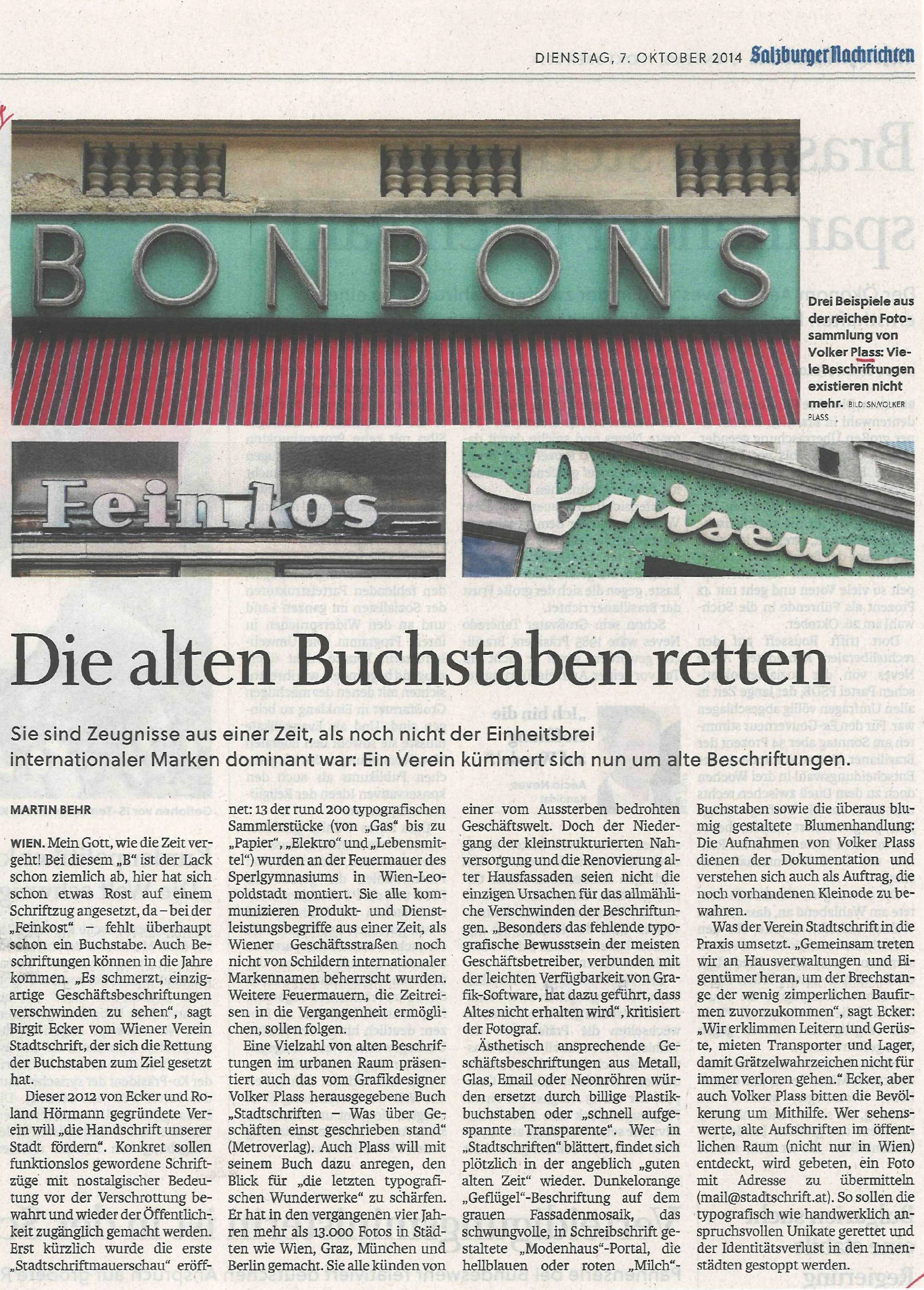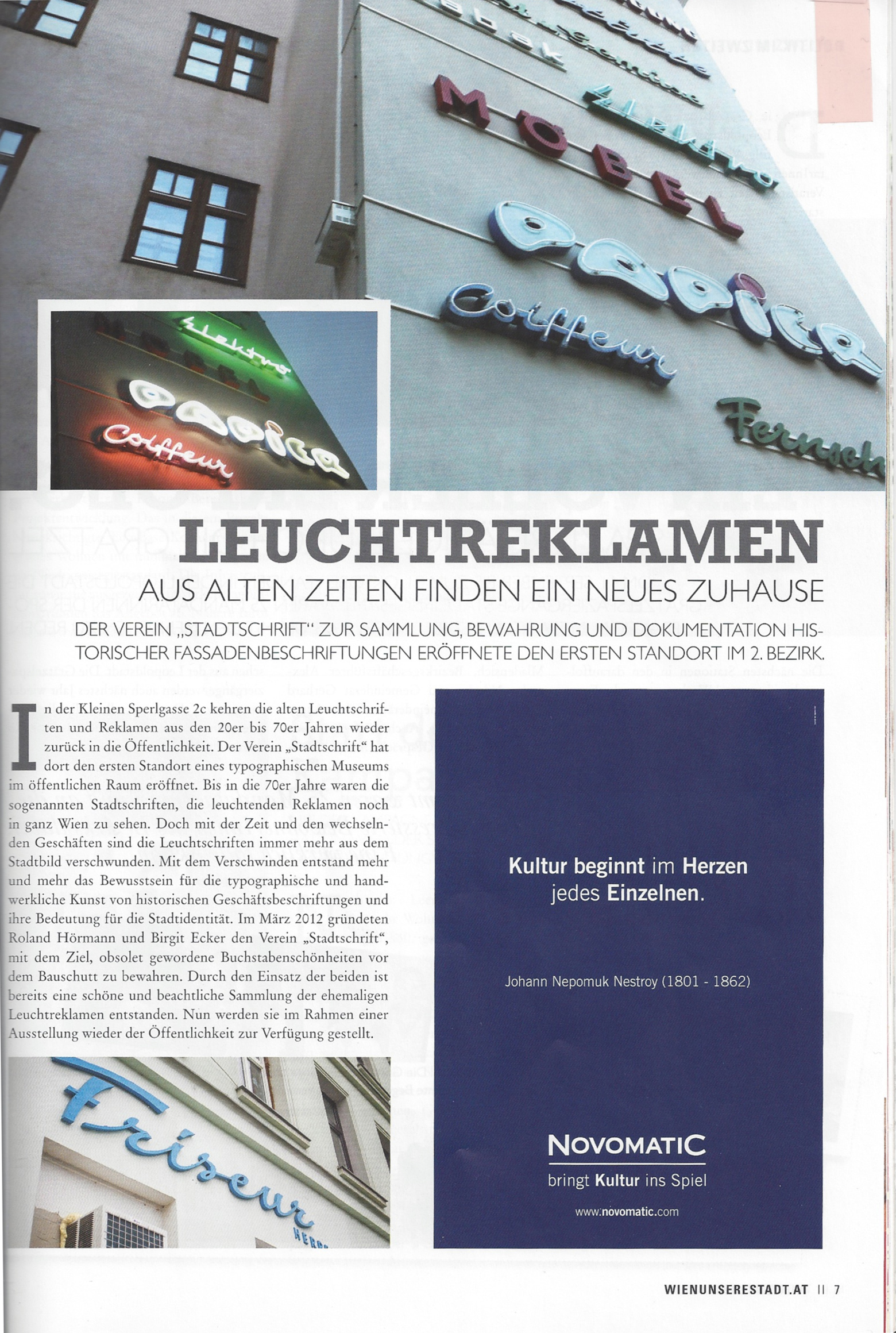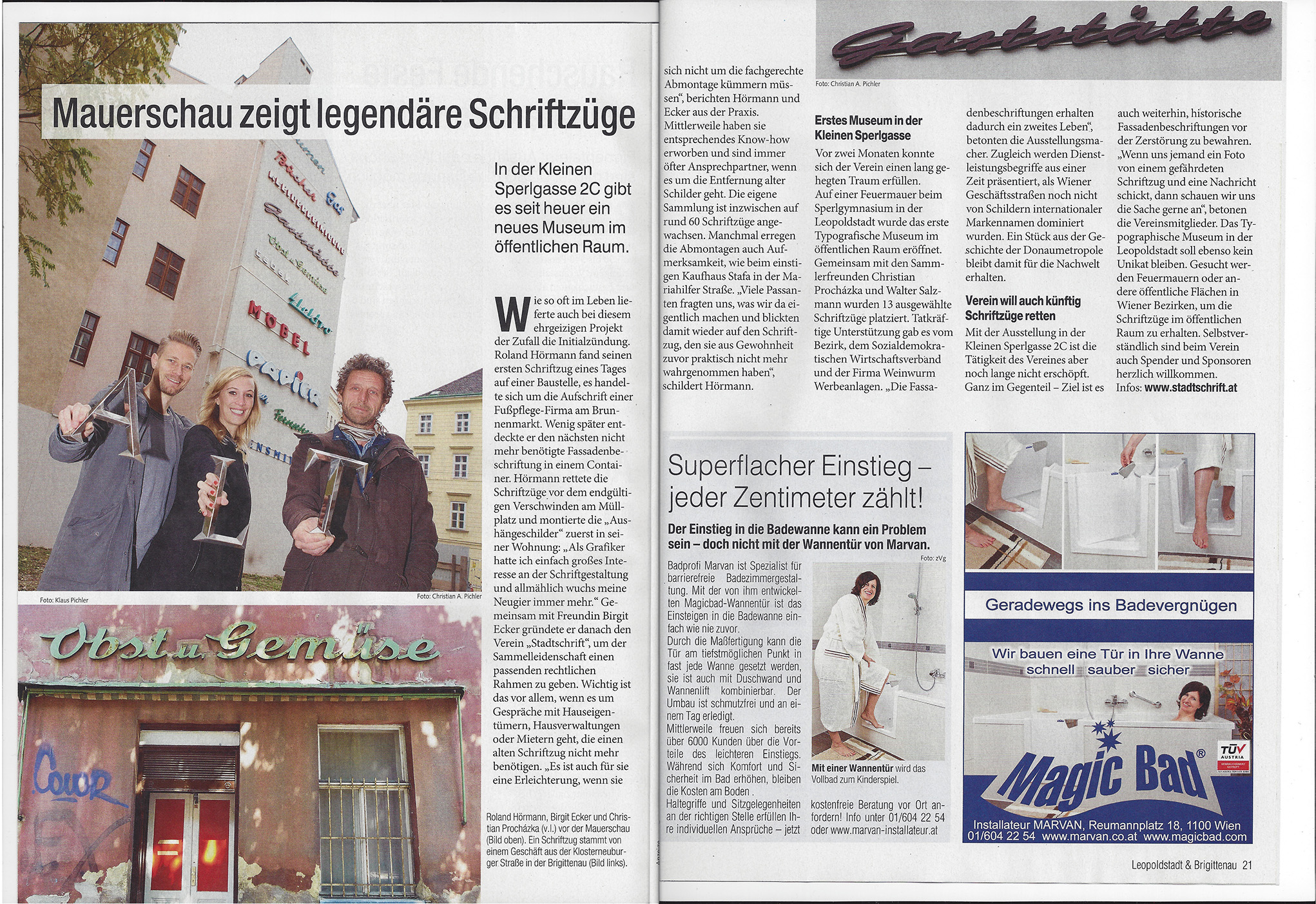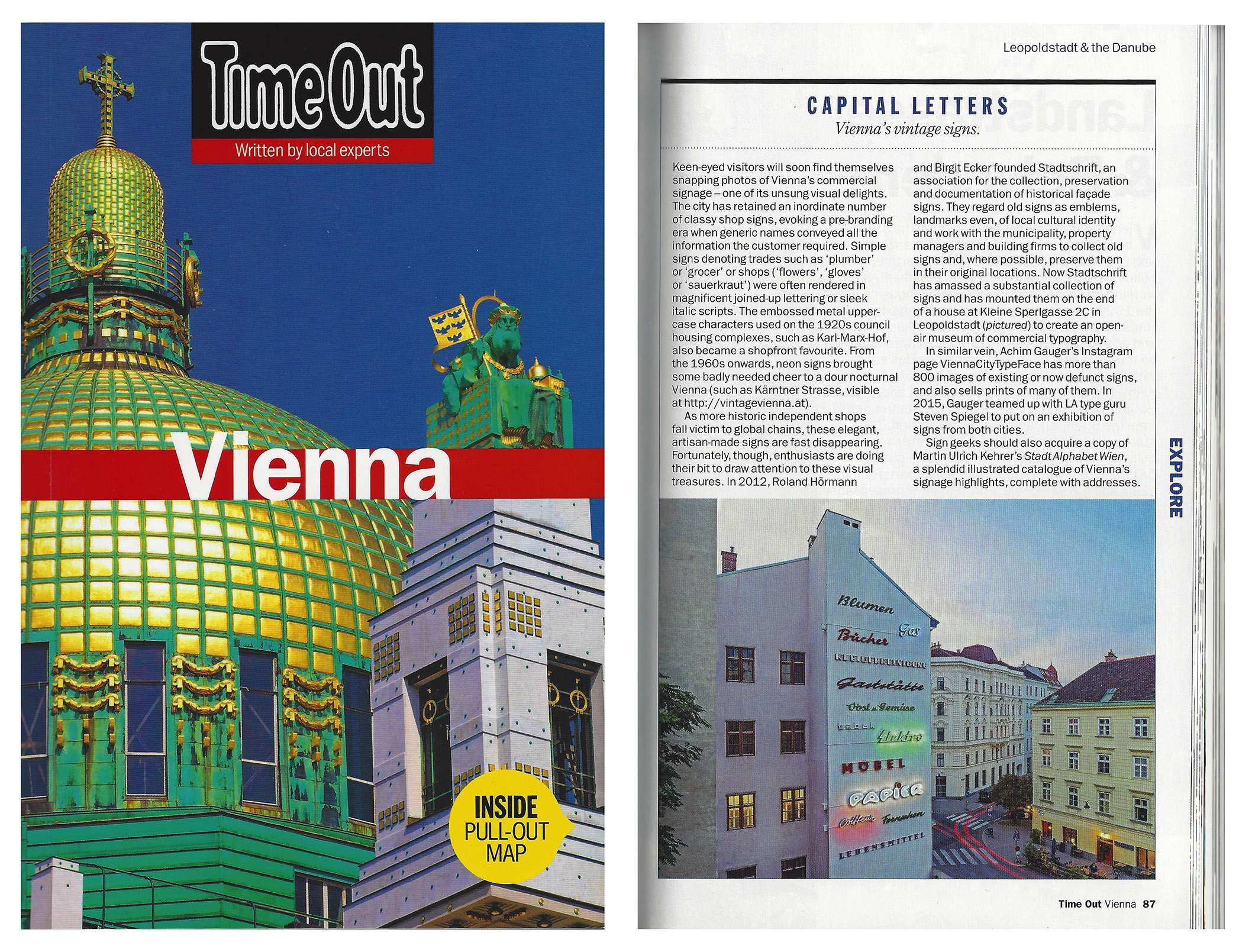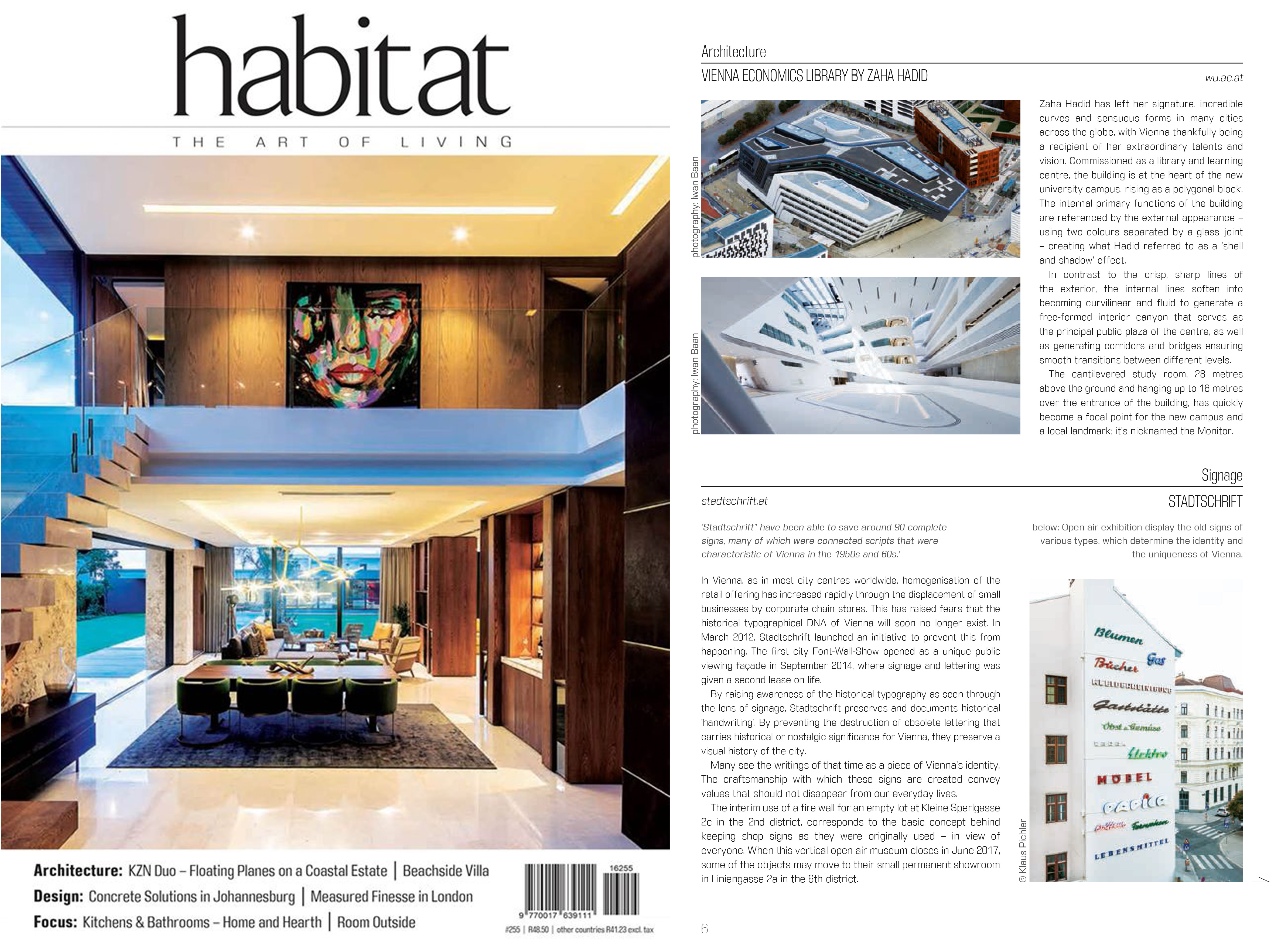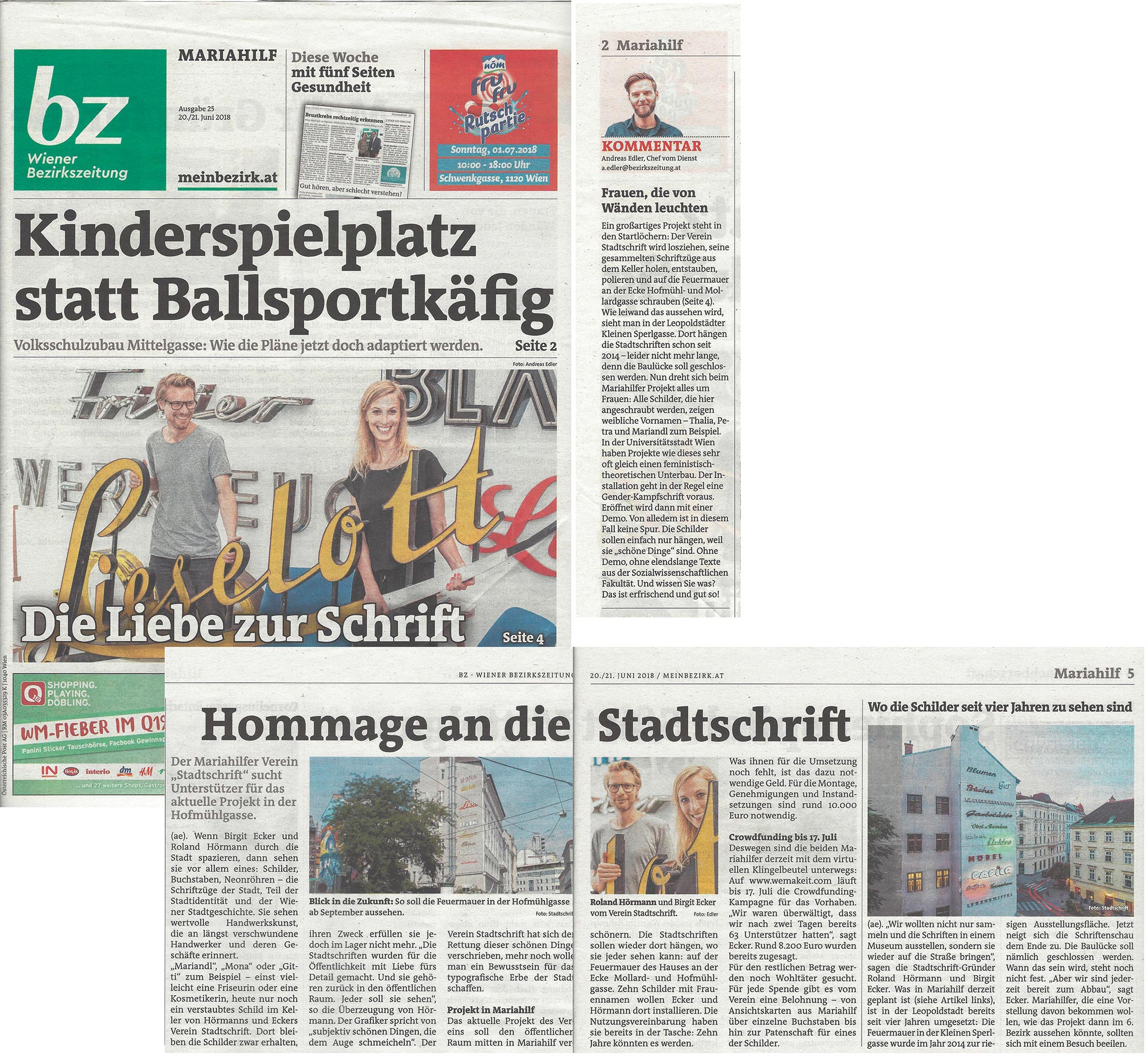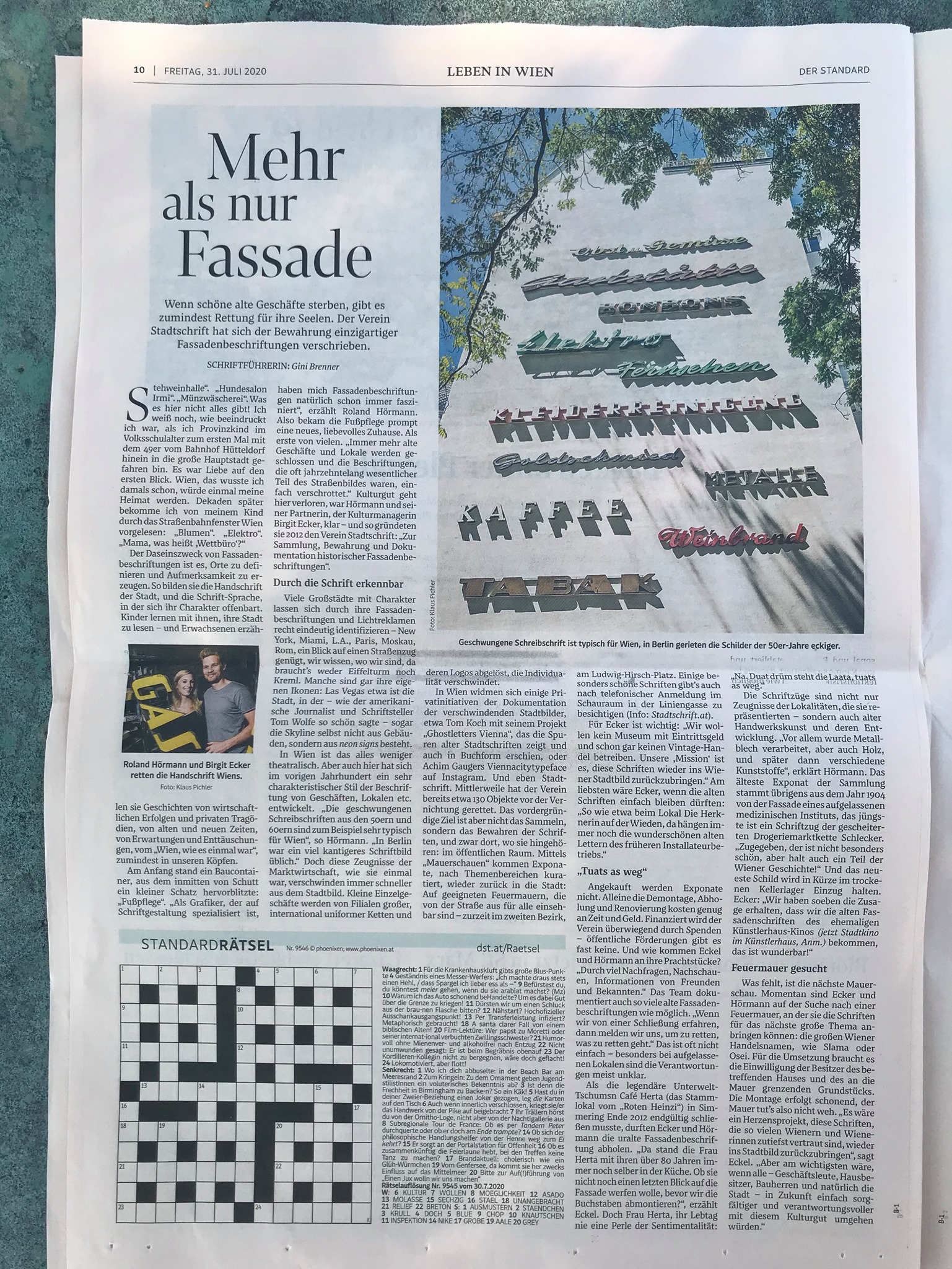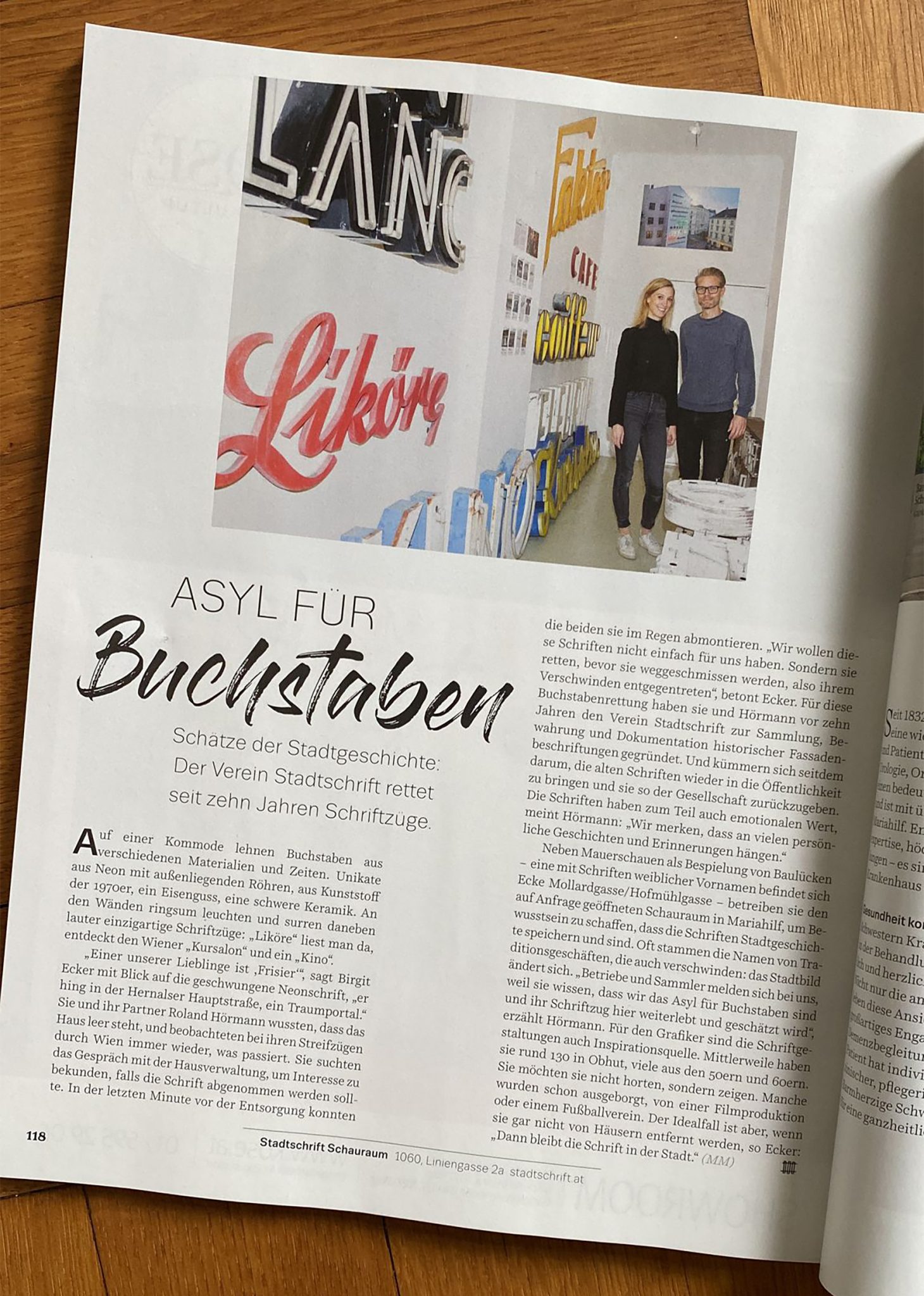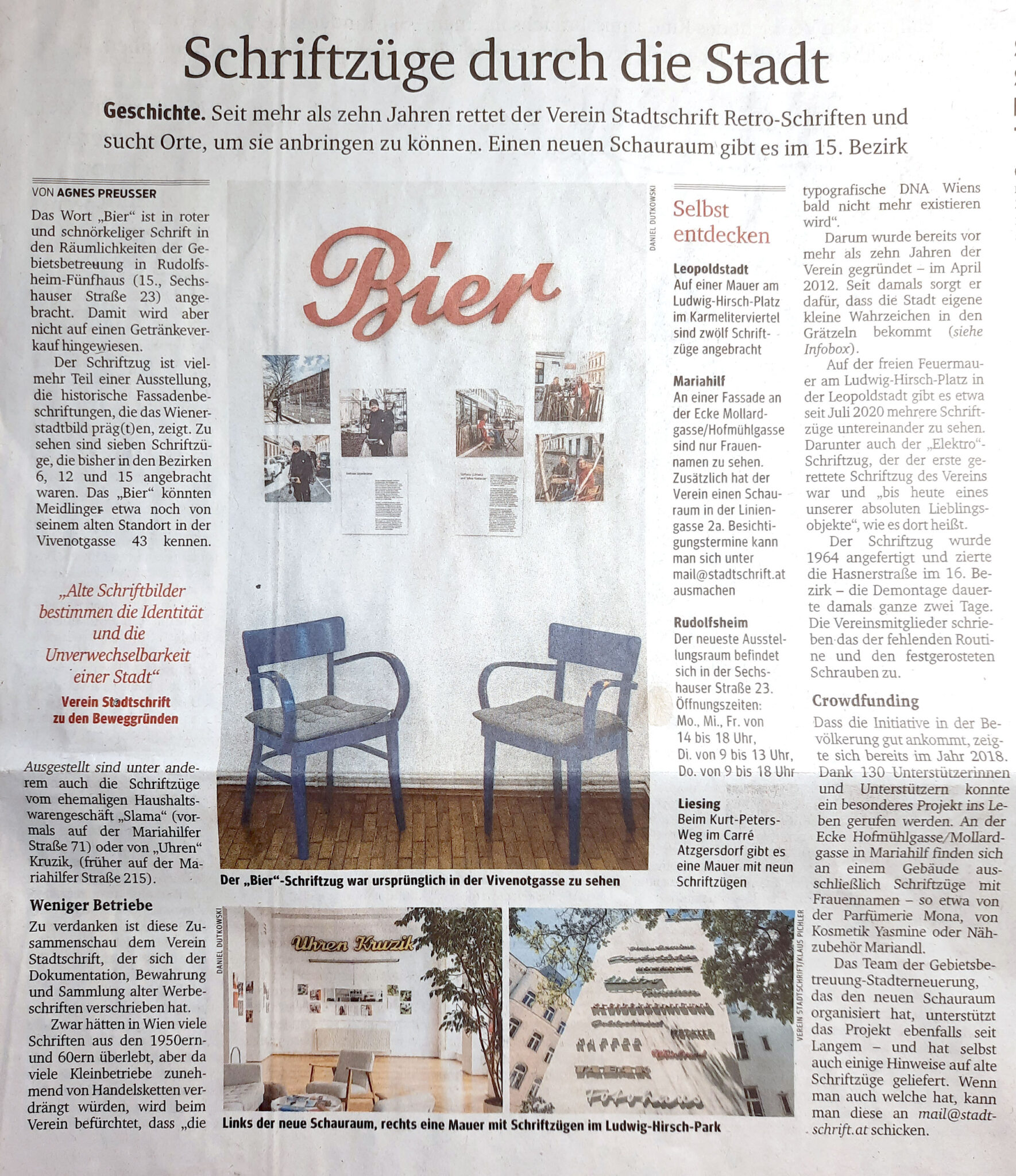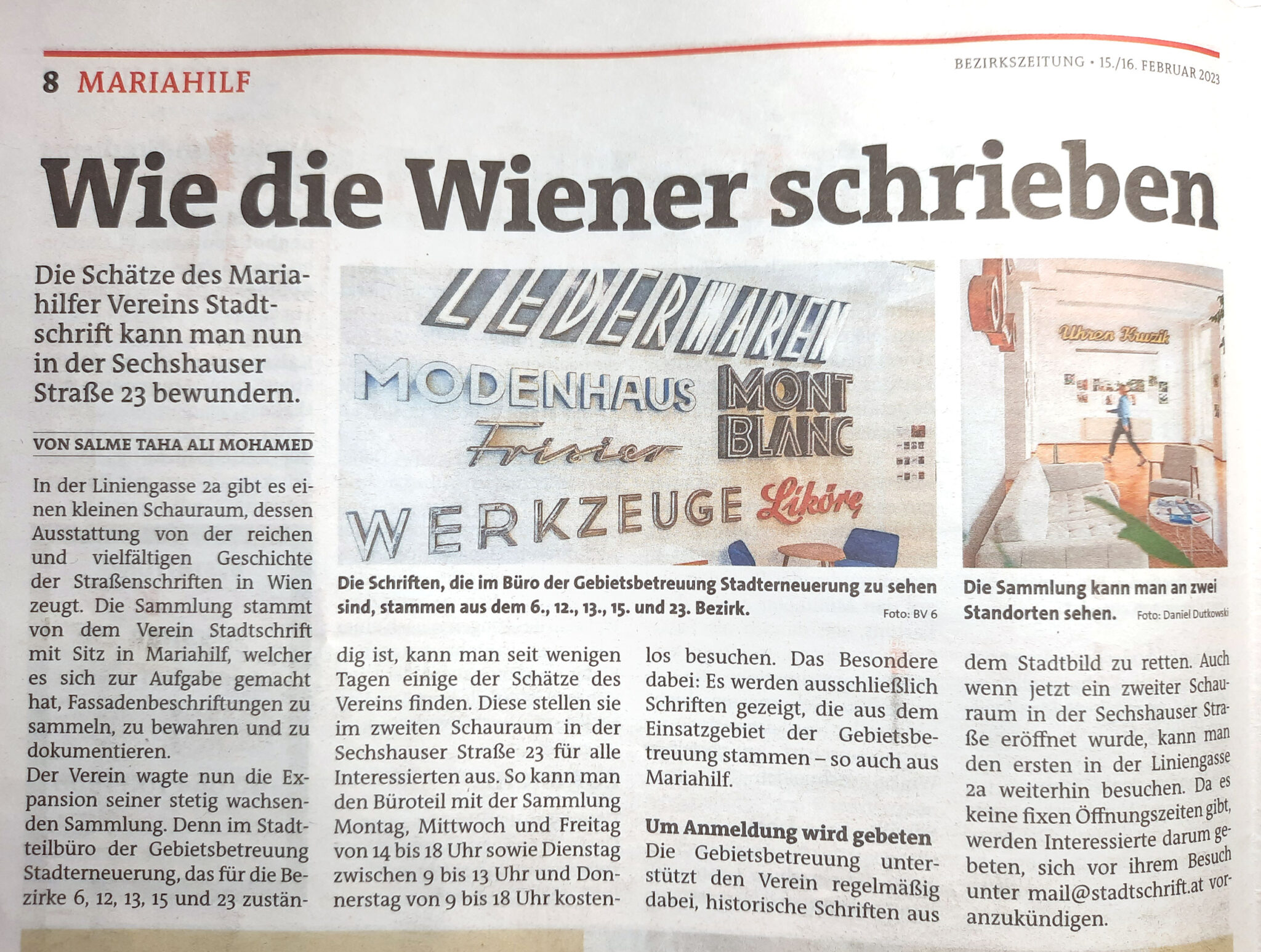
»A walk around Vienna offers a lush typographical history. […] In 2012 lettering enthusiasts founded an association, the mission of which is to preserve old signage and its legacy.«
Monocle Magazine, UK, July/August 2016
»They regard old signs as emblems, landmarks even, of local cultural identity and work with the municipality, property managers and building firms to collect old signs and, where possible, preserve them in their original locations.«
Time Out „Vienna“, UK, 2015
»Irgendwann wäre ein Großteil davon verloren gegangen, wenn der Verein Stadtschrift nicht die besonders charmanten, attraktiven oder handwerklich wertvollen vor der Müllhalde bewahrt hätte.«
Die Presse „Schaufenster“, Juni 2015
»Der Verein Stadtschrift hat sich der ausgedienten Schriftzüge in Wien angenommen und will sie der Öffentlichkeit zurückgeben. Ein steiniger Weg, aber bereits mit sichtbarem Erfolg«
orf.at, 26. Dezember 2014
»Die Seele der Stadt als Museum an der Wand«
Wiener Bezirksblatt, 27. Oktober 2014
»Sie sind Zeugnisse aus einer Zeit, als noch nicht der Einheitsbrei internationaler Marken dominant war.«
Salzburger Nachrichten, 7. Oktober 2014
»Elektro und Lebensmittel statt Saturn und BILLA«
Der Standard, 25. September 2014
»Netter Schriftzug: Eine Initiative rettet Buchstaben vorm Verschrotten und zeigt jetzt die Stadtschrift in einer Ausstellung«
Falter, 13. November 2013